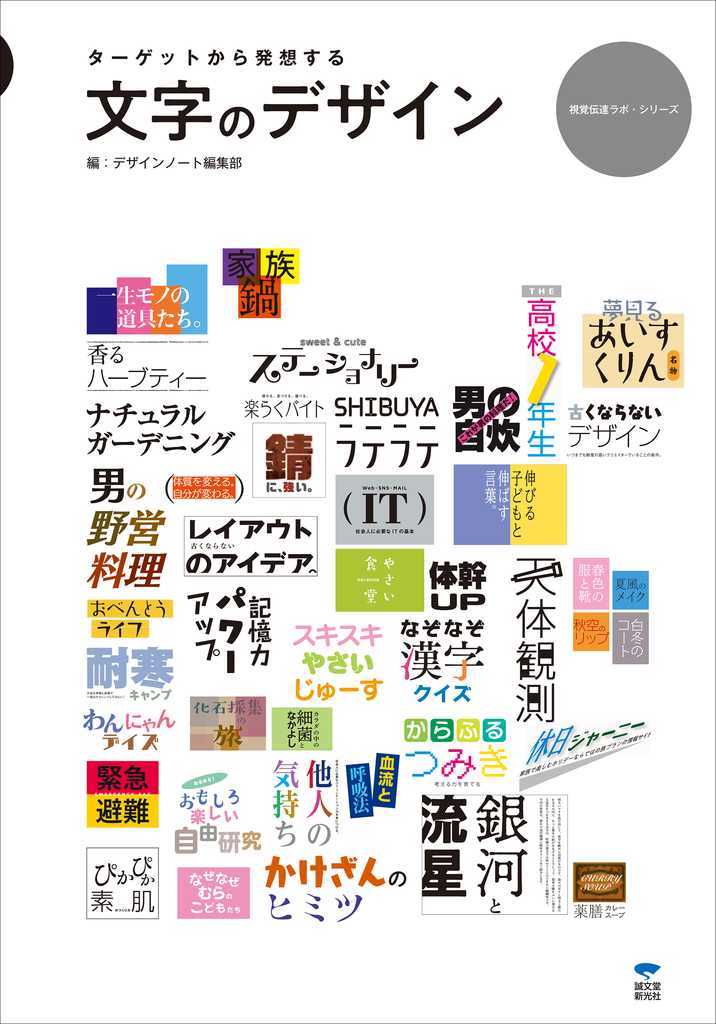
文字のデザイン―ターゲットから発想する
グラフィックデザインにとって避けて通れないのが文字の表現である。
文字を適切に使うことによりクライアントや消費者といったターゲットにズバリと刺さるデザインにブラッシュアップできる。その方法が学べる「文字のデザイン―ターゲットから発想する」が、最新のデザインの表現と思考のプロセスを追う、デザインの専門誌(MOOK:隔月刊)「デザインノート」編集により、誠文堂新光社から2019年1月8日(火)に刊行された。
「文字のデザイン―ターゲットから発想する」では、クライアントからのあらゆるタイプ要求に答えた数多のデザインサンプルとそのデザインした理由を紹介。
デザインによって誰が誰に何をいつ、どこで、なぜ伝えるかに言及することで、ビジュアル表現の答えをつかみ取ることができる一冊。
自分の好きなフォントで、タイトルなどの文字組を行ってみるとフラットな印象で物足りなさを感じることがあるが、やみくもに変形してみたり、多くの色を使うことで強調できたと思っても、デザインとしてはうまくいかない。クライアントから「もっとダイナミックに」とか「もっとかわいく」とか「もっとクールに」などの要望があった場合、どのように対処をするか、「文字のデザイン―ターゲットから発想する」では、「ターゲット」というデザインが向かうべき方向性や「きっかけ」、「文字」にまつわるさまざまな手法を駆使したデザインを行うアイデアをデザイナー初心者だけでなく、デザインに興味のある一般の方々にも分かりやすく、直感的に理解できる作例を中心に構成を心掛けて編集された。デザイン処理や加工事例をふんだんに盛り込んでいるので、プロにもアイデアソースとして役立つ内容で、出版や企業の広報、宣伝、ブランディングに関わる方々にも大いに参考になる一冊。